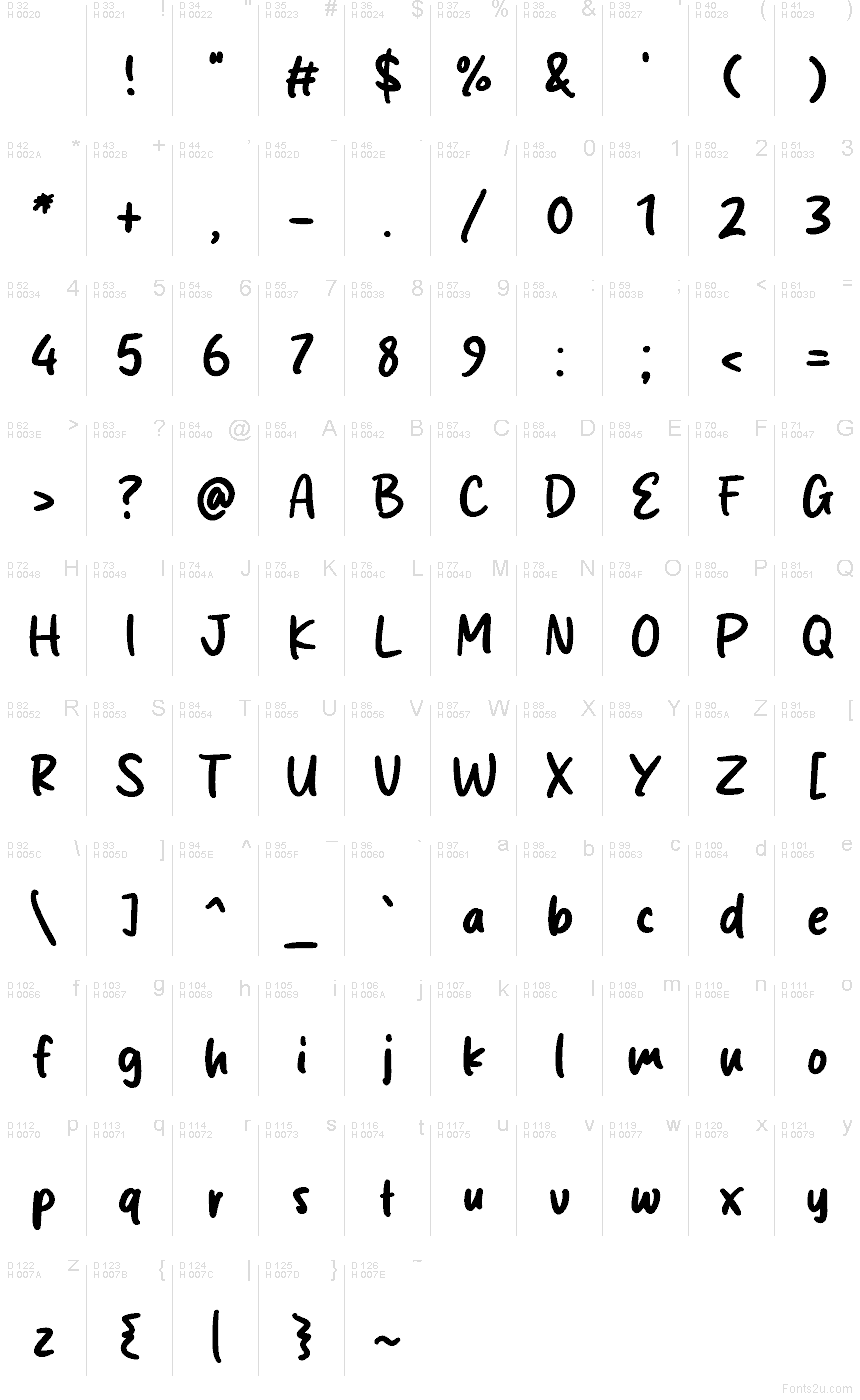
Swallow Balloon von MJType ist eine kostenlose Handschriftart mit hohen, federnden Buchstaben und einer lockeren Linienführung wie von einem Marker. Wechselnde Strichstärken, abgerundete Bögen und leicht ungleichmäßige Proportionen verleihen dem Schriftbild einen flotten, persönlichen Charakter.
Als sympathische, handgezeichnete Beschriftung passt sie hervorragend zu Verpackungen für Cafés. Dieselben lockeren Formen eignen sich auch für das Branding ungezwungener Gastronomieangebote, Plakate für Kinderveranstaltungen und heitere Grafiken für soziale Medien mit kleinen Doodles. Verpackungen sind ihr stärkstes Einsatzgebiet, da die weichen Rundungen Produktnamen eine hausgemachte, nahbare Note verleihen.